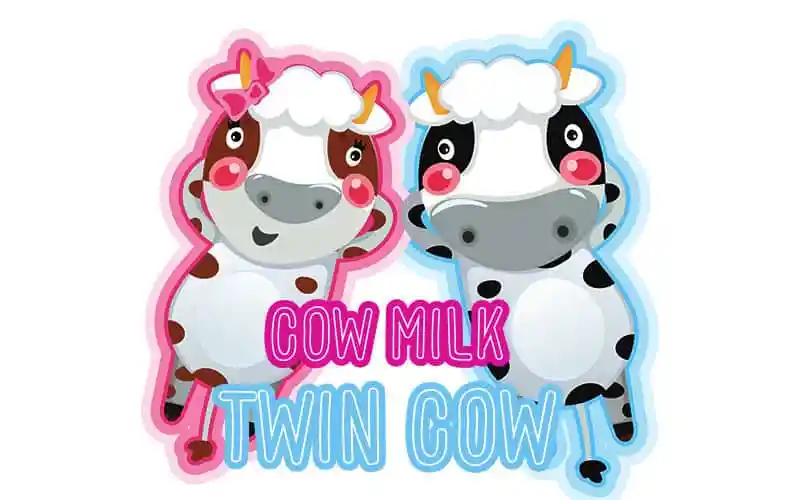
Coco Milk Display Font
A Coco Milk Display Font é uma escolha ideal para arquitetos digitais que buscam um toque charmoso em suas criações. Com influências das caligrafias tradicionais, mas com uma sensação fresca e contemporânea, essa fonte manuseia proporciona tanto a classe quanto a versatilidade necessária. Ela não apenas atende aos requisitos de design para letra de papel, cartão-postal e logotipo, mas também se adequa perfeitamente às demandas mais criativas do atual mercado digital. Ideal para quem busca um toque divertido sem perder seu glamour, a Coco Milk Display se destaca como uma fonte casual que não só enriquece as suas criações digitais com sua beleza singular, mas também pode ser facilmente adaptada e personalizada conforme necessário. Uma escolha inteligente para os criadores de design online e impressos que buscam um toque elegante e fresco em seus trabalhos.